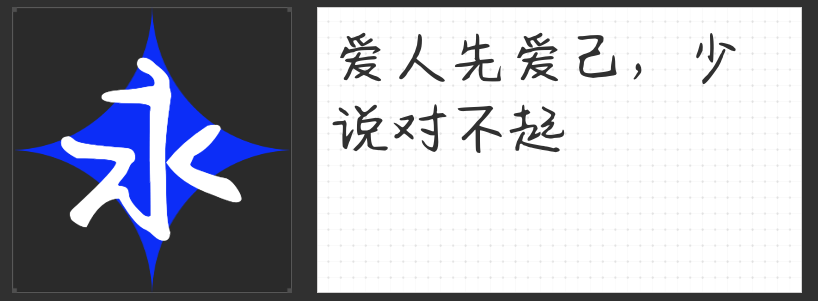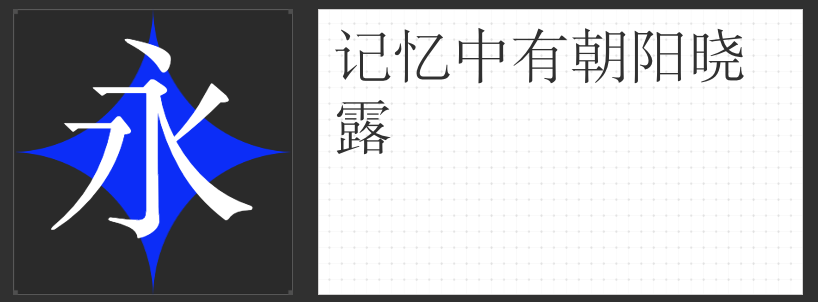
四款匠心字库字体推荐:内嵌设计的品质之选
在数字化设计领域,字体的选择往往决定着作品的视觉调性与情感表达。对于需要内嵌字体的项目而言,一款兼具美学价值与实用性的字体,不仅能提升整体设计质感,更能精准传递信息内核。以下四款专业字库字体,以独特的设计语言与广泛的应用适配性,成为内嵌场景中的理想之选。
一、MyFont爱你老己简 微黑
这款手写字体以“随性而不失章法”为核心设计理念,通过自然连贯的笔画形态与轻快的运笔节奏,将生活化的书写场景转化为视觉语言。其字形结构保留了手写特有的微小起伏与笔锋转折,既不过分规整而显呆板,亦不因过度潦草而失辨识度。这种介于严谨与自由之间的平衡感,使其在包装、封面等需要营造人文氛围的场景中表现尤为出色。
二、励字书宋简繁
作为正宗老宋体的当代演绎,这款字体延续了横轻竖重、结构匀称的经典特征,却在细节处融入现代审美考量。其笔画粗细过渡自然,字面布局疏密有致,既保留了宋体特有的书卷气与仪式感,又通过优化中宫结构提升了小字号下的可读性。无论是传统出版物内页,还是需要传递权威感的正式文档,均能以典雅气质彰显内容价值。
三、励字魔方黑简
以几何方块为设计基底,这款无衬线字体通过方头方尾的笔形与强烈的粗细对比,构建出极具现代感的视觉框架。其字形简洁到近乎抽象,却因精准的笔画比例与空间分割而保持了良好的识别性。这种“少即是多”的设计哲学,使其成为信息层级梳理、标题重点突出的利器。
四、励字志向黑简 超粗
针对数字屏幕的显示特性,这款超粗字体创新性地融合圆体与黑体特征,通过外圆角处理软化了传统黑体的生硬感,同时以饱满的字面与稳定的结构确保了远距离辨识度。其设计兼顾了视觉冲击力与阅读舒适性,尤其适合移动端界面、户外广告等需要强吸引力的场景。